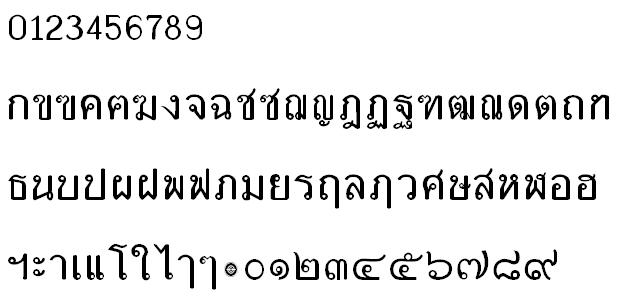
ขออนุญาติจ้างทำฟอนต์10000
จากในแบบฟอนต์ที่คุณกอล์ฟให้มา ตัวอักษรแต่ละตัวจะถูกบล็อกให้มีความกว้างเท่ากัน แต่หลังจากที่ทำออกมาแล้ว ทั้งตัวอักษร สระ วรรณยุกต์ แม้ไม่มีปัญหาเรื่องตีกัน แต่ตามความเห็นผู้ทำแล้ว มันไม่สวยเอาเสียเลย
จึงเรียนมาเพื่อทราบและขอยาดเปลี่ยนแปลงแบบไม่มีเงื่อนไข